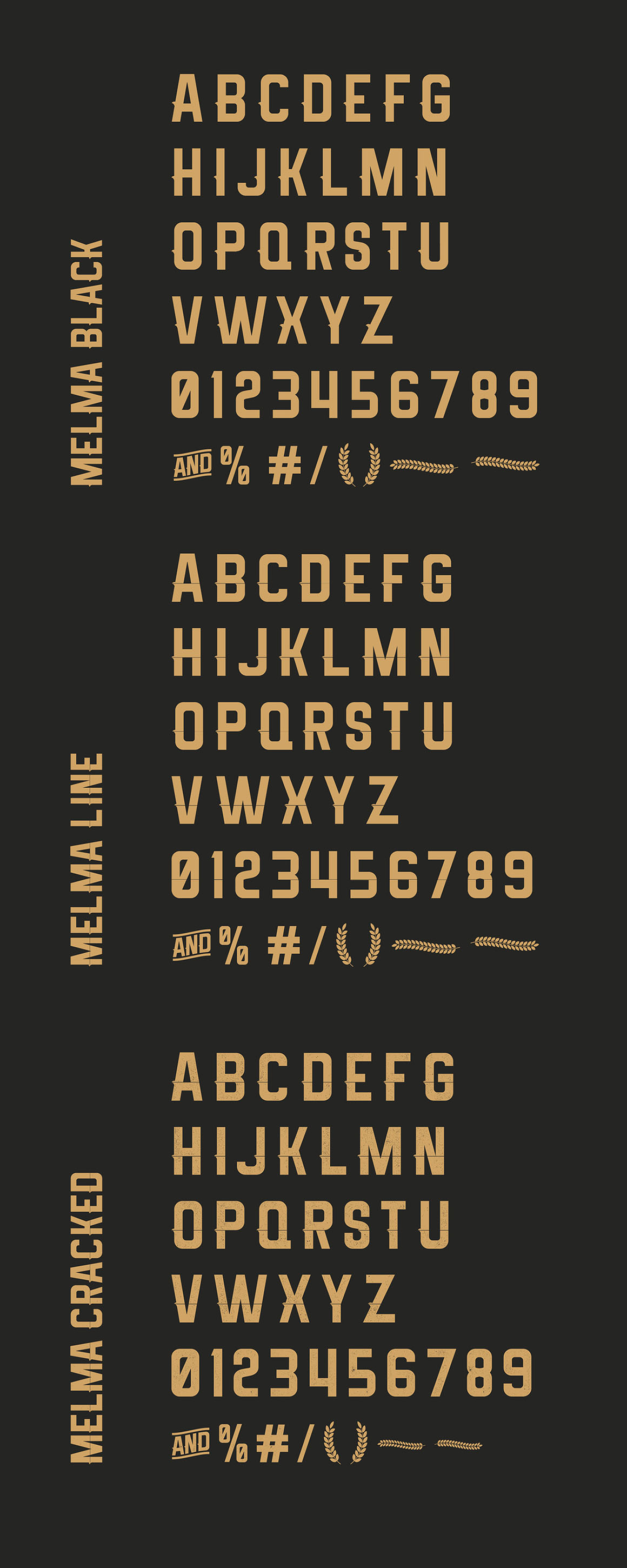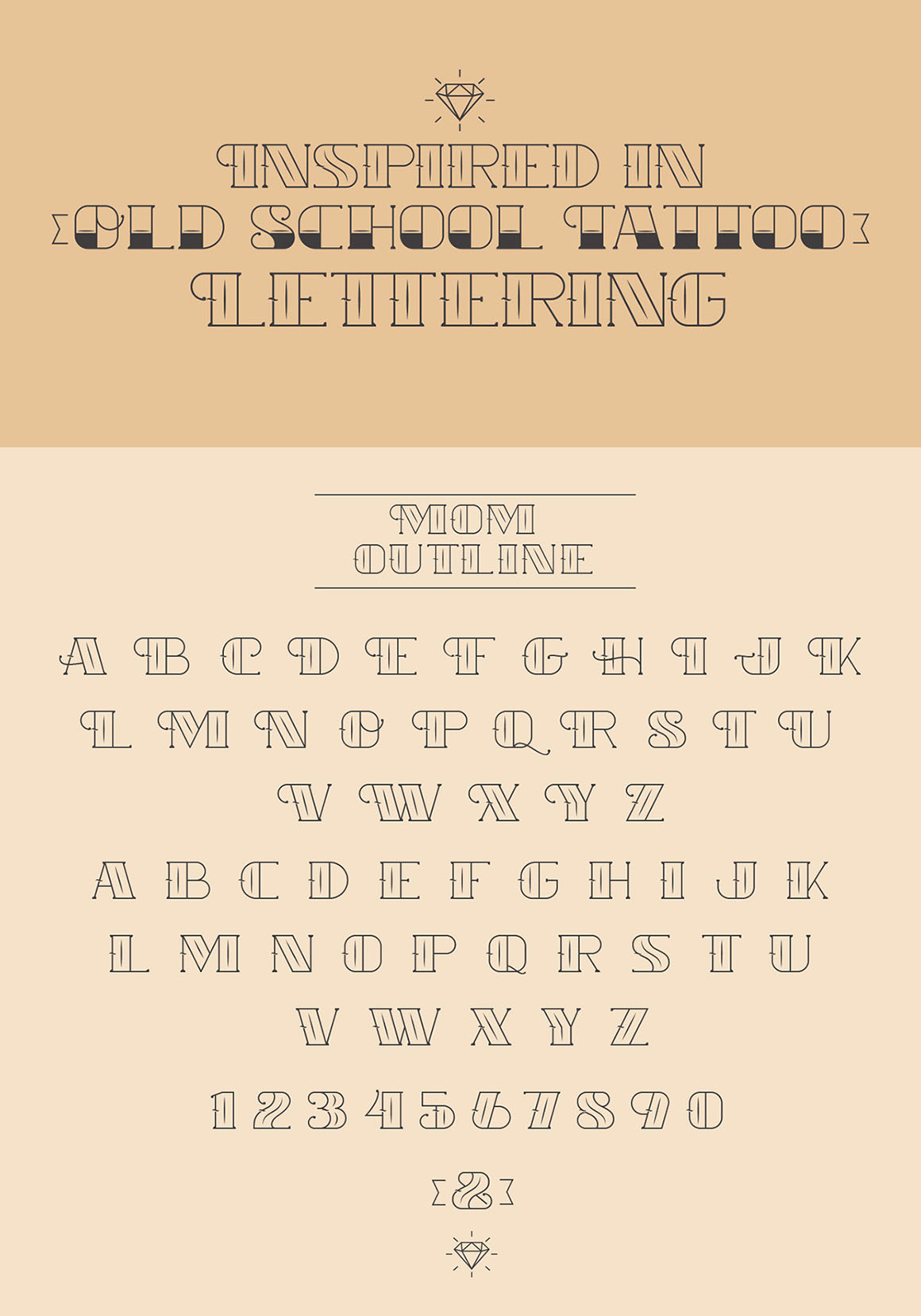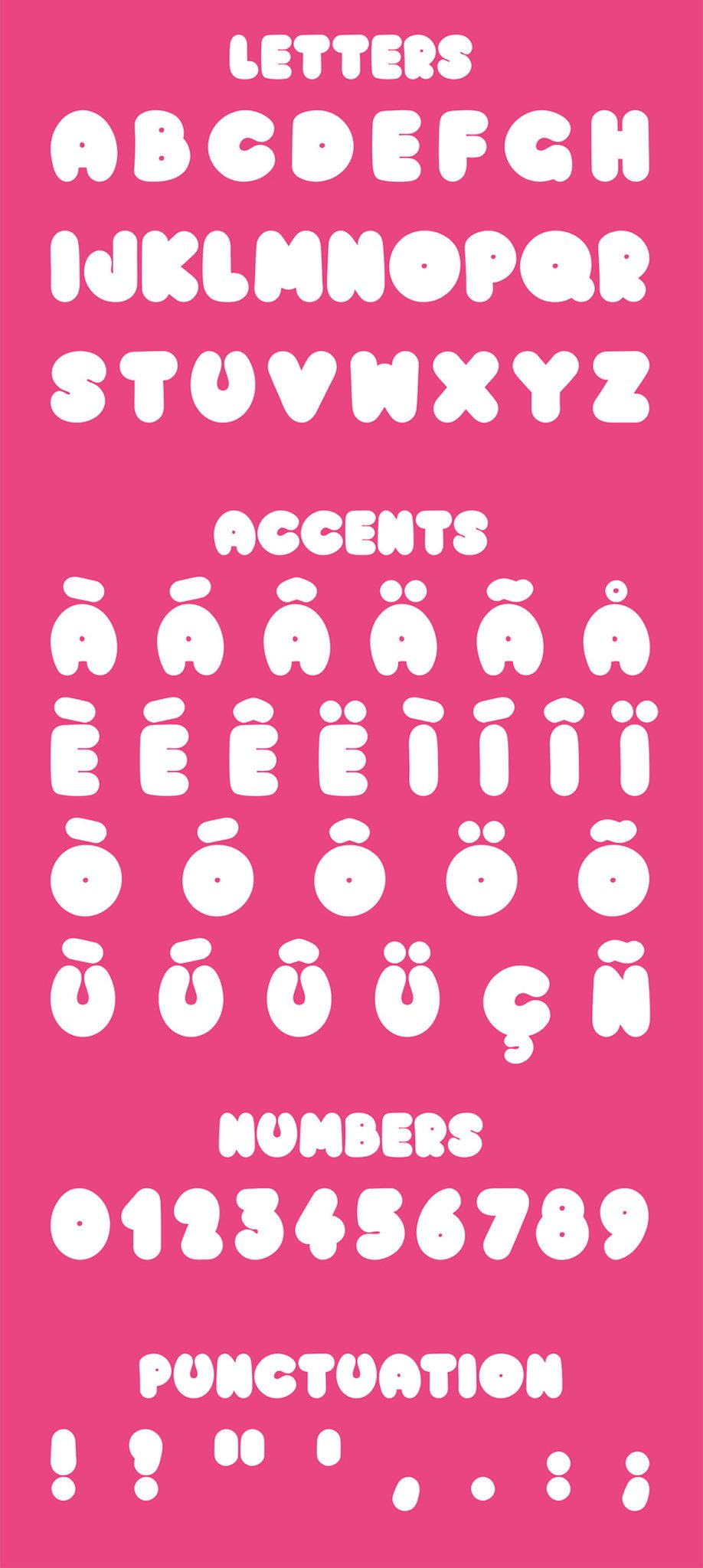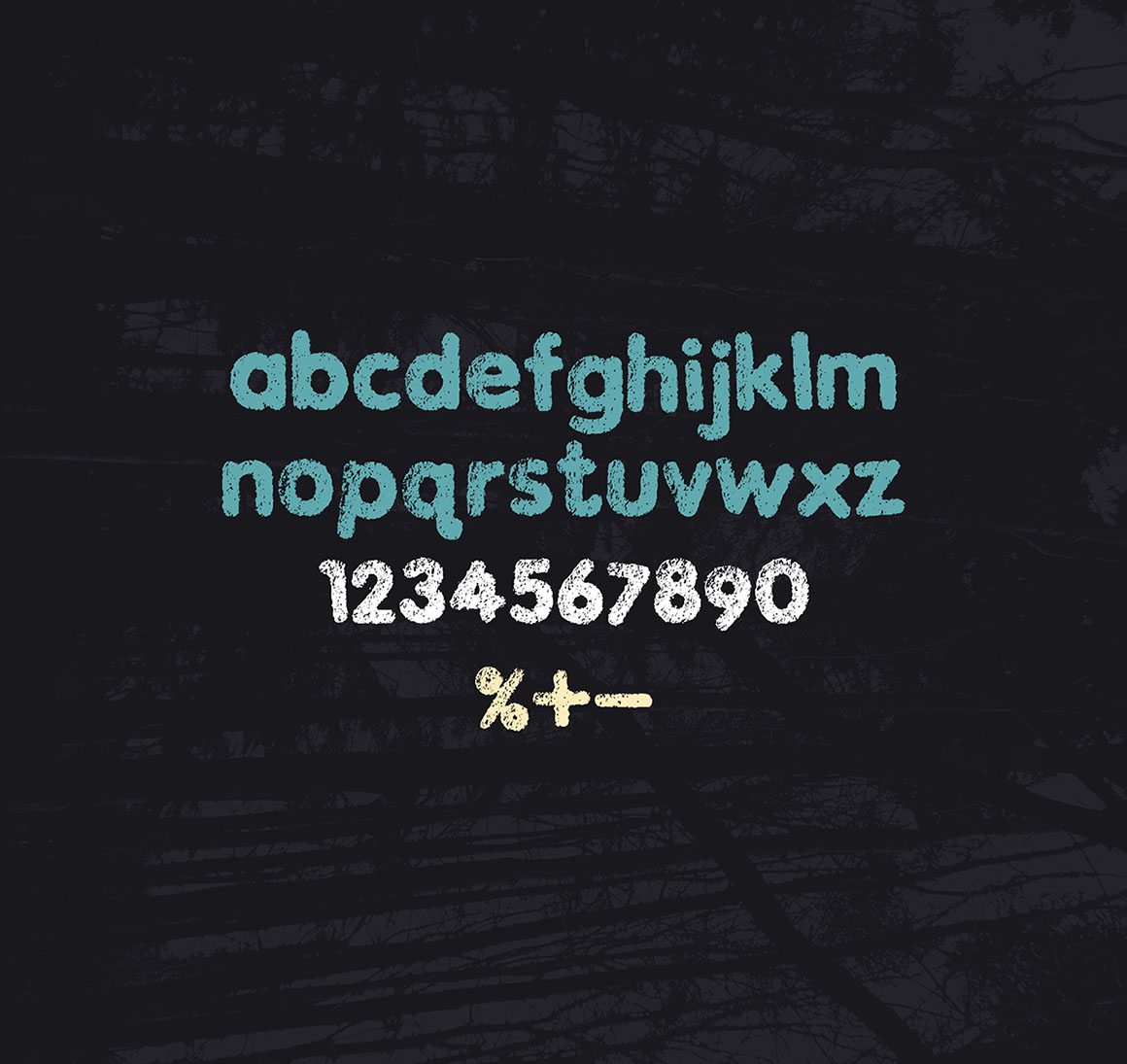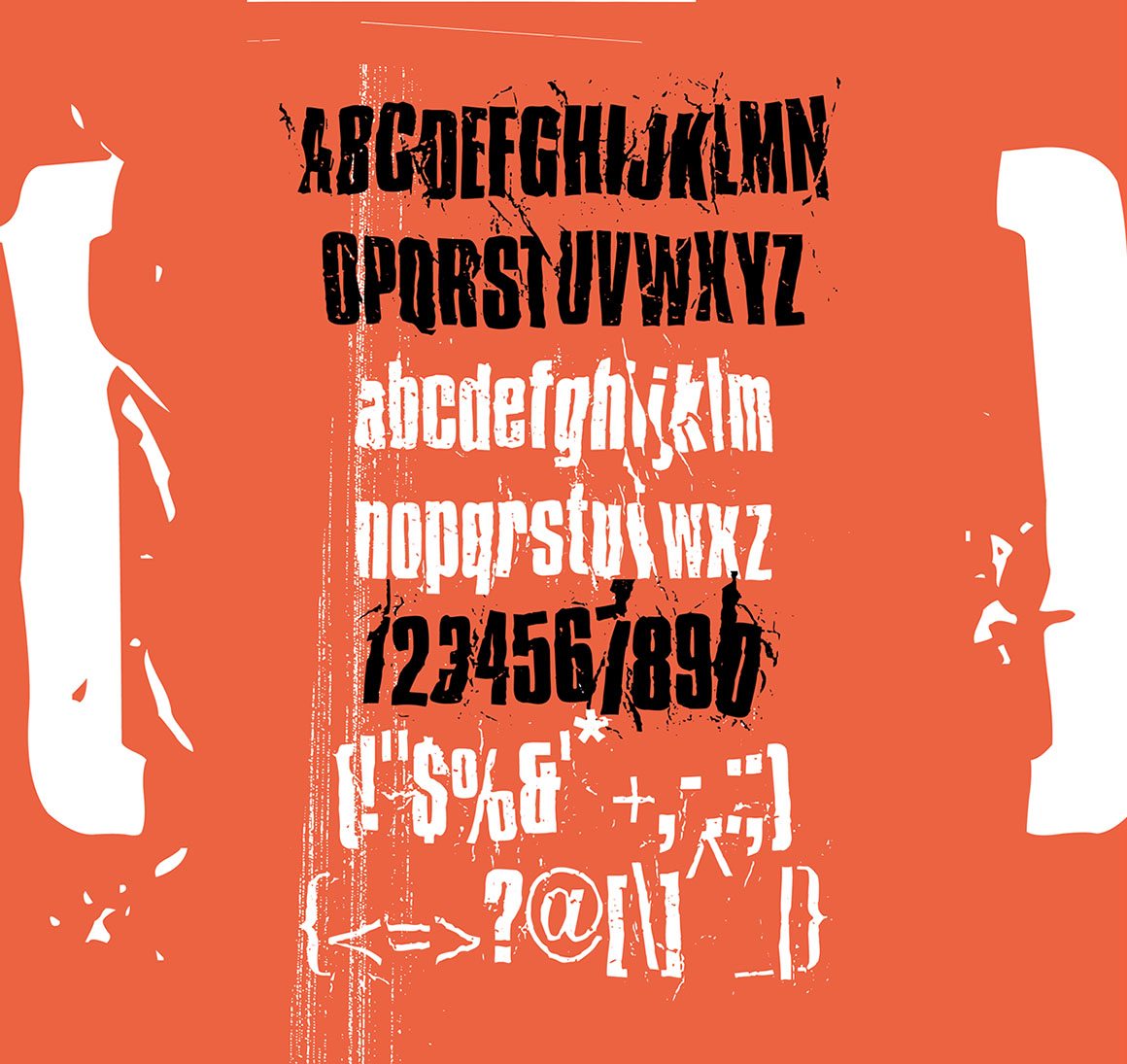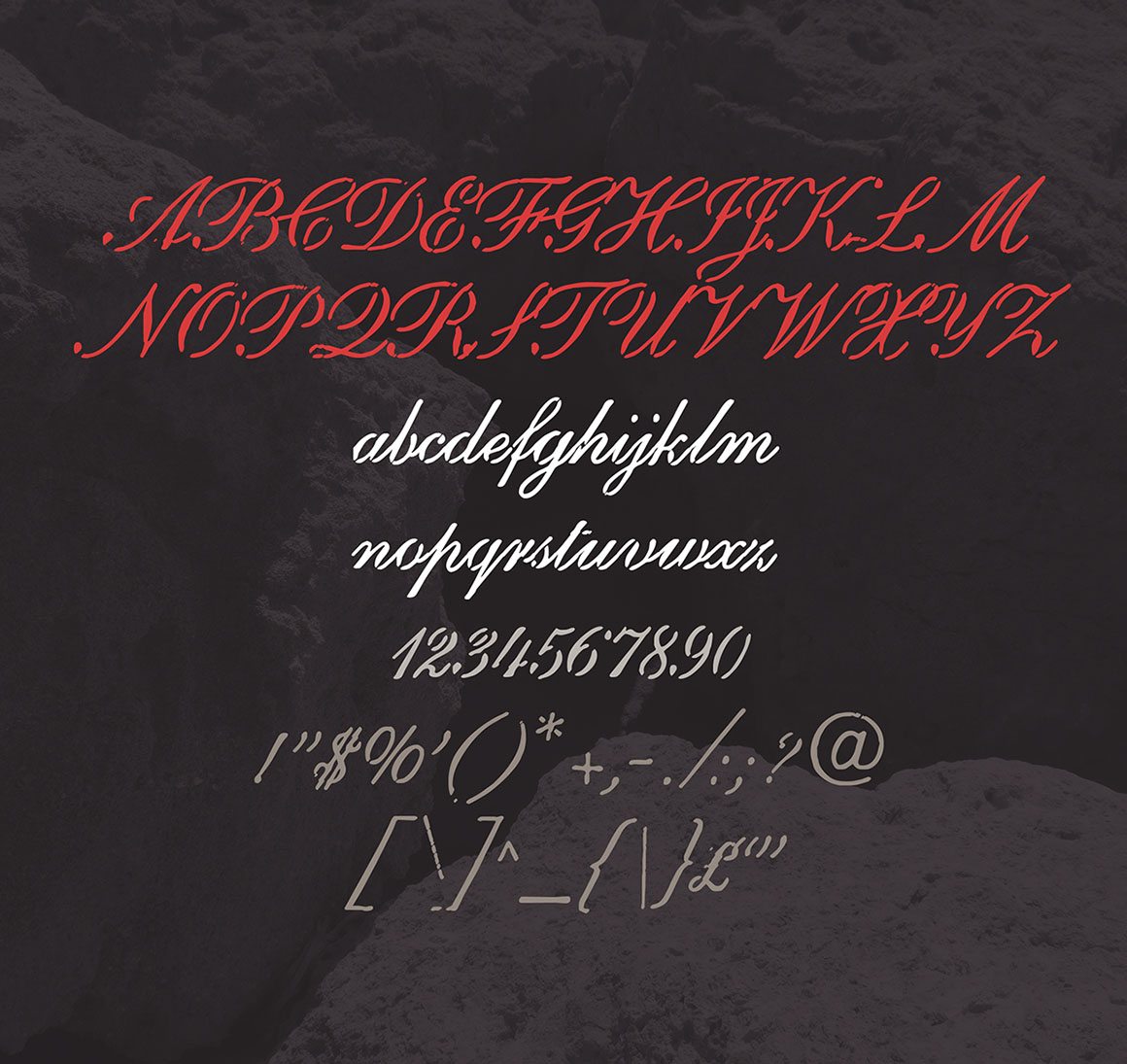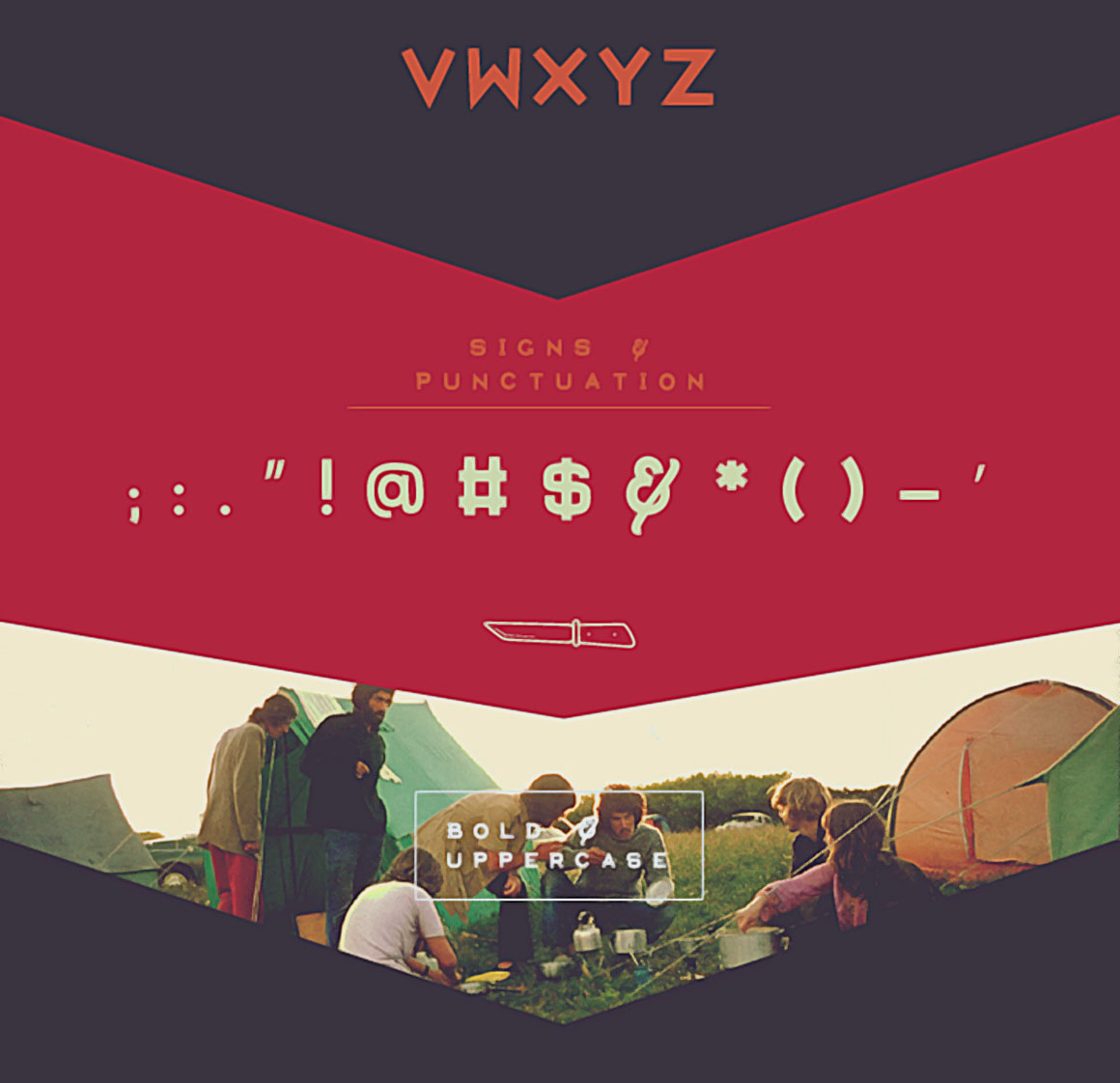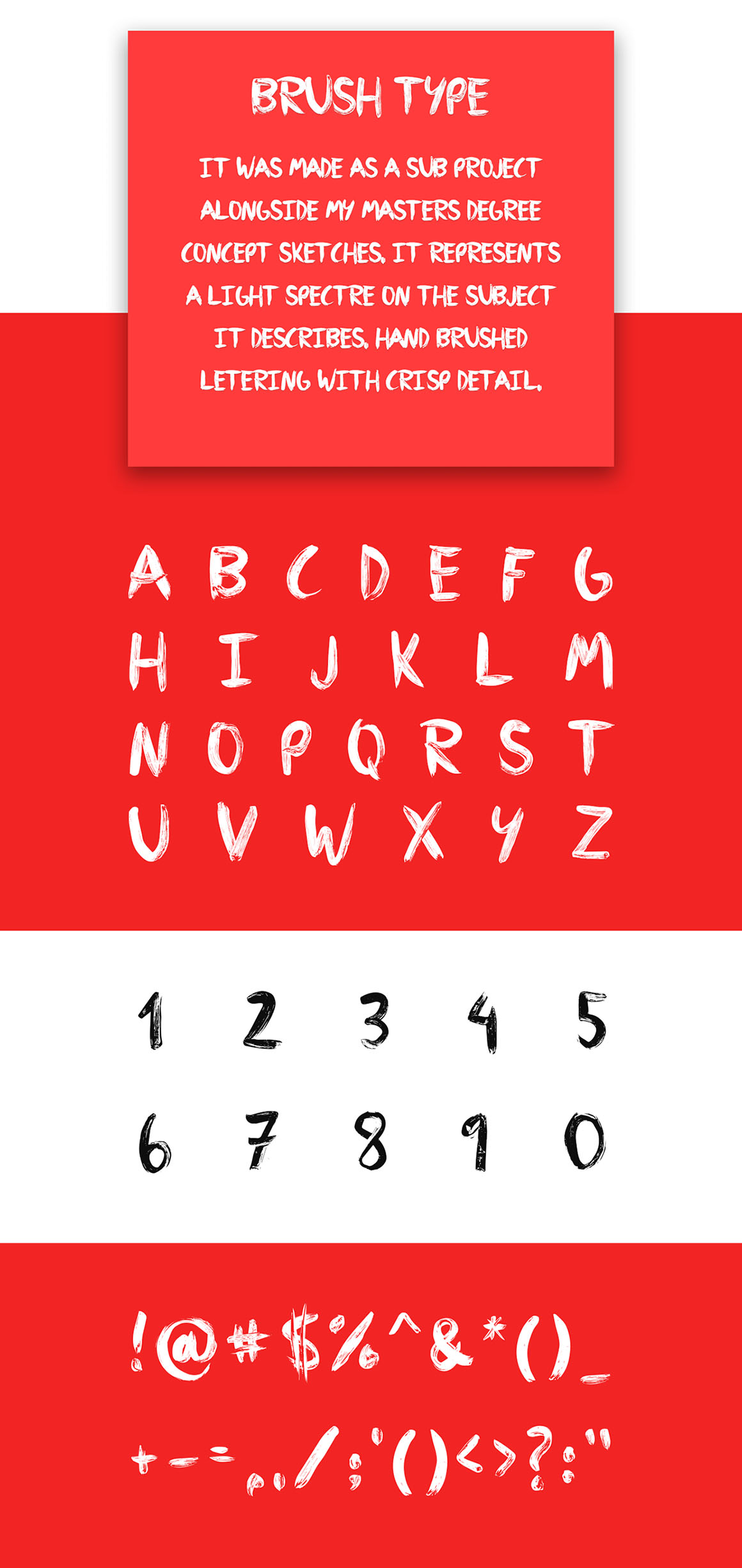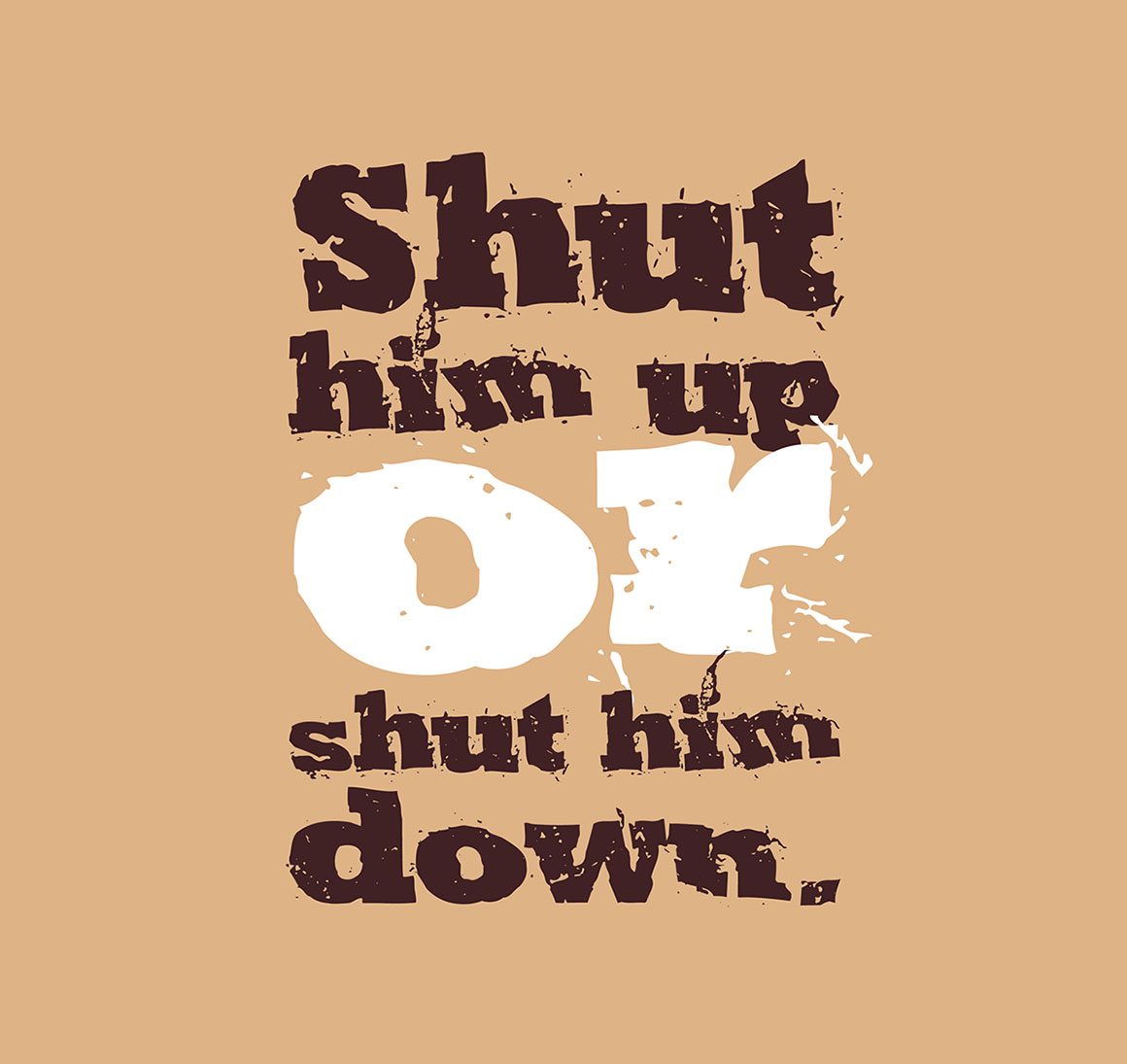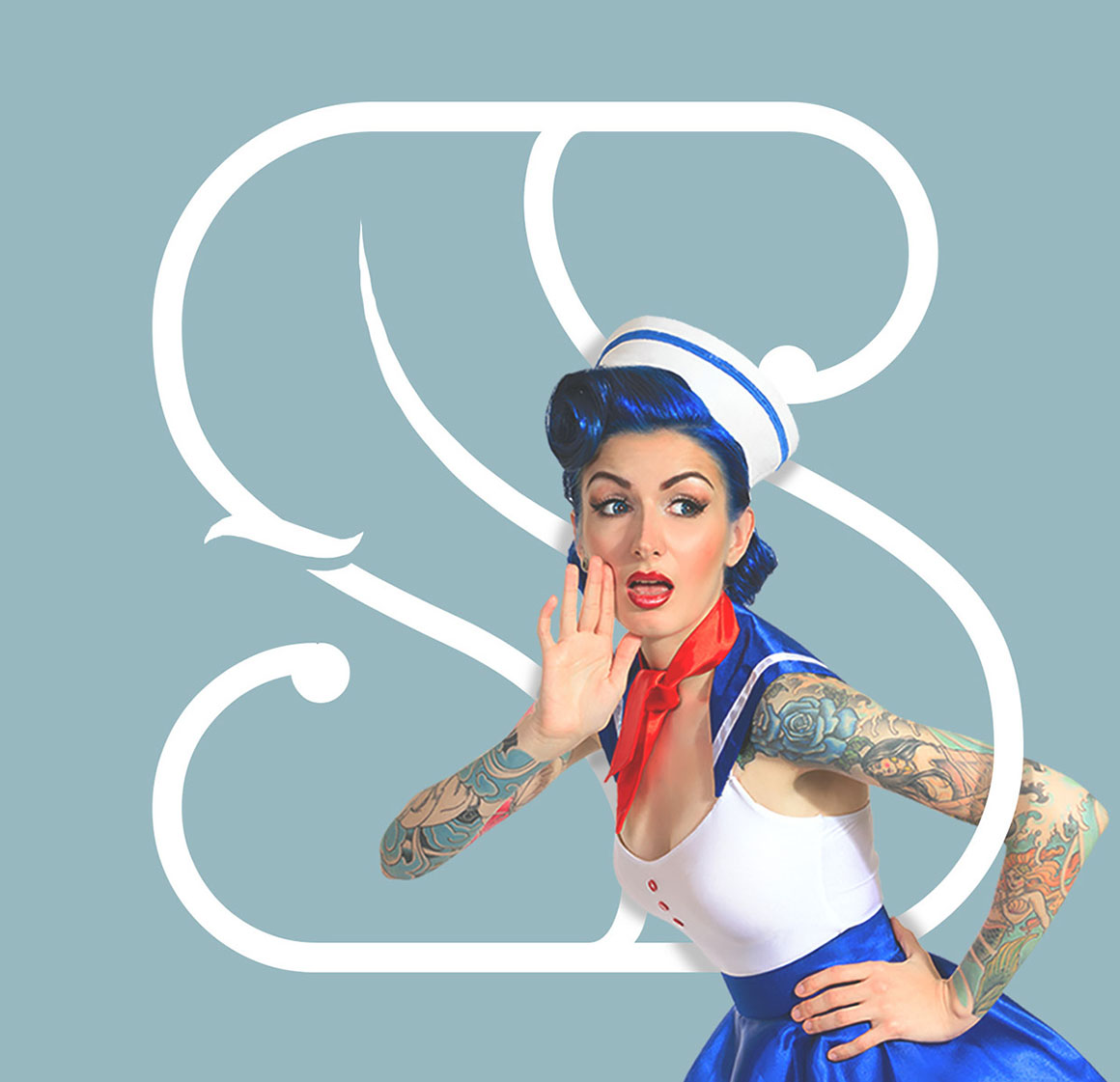
November Sources: Free font novembre 2015
1. Dreamers Brush – Free Font by Get Studio
Questo tipo di carattere tipo pennello,  freddo e urbano è di Get Studio. Ottimo per le tue nuove opere d’arte in stile creativo. Scarica e godi;)
2. Banthers – Free Vintage Font by Agga Swist’blnk
Questo font stile retrò è di Agga Swist’blnk. Un carattere tipografico con un sorprendente stile vintage tutto maiuscolo. Contenente anche un set di caratteri speciali.
3. Fabfelt – Free Script Font by Fabien Despinoy
Questo fresco carattere script gratuito, disegnato a mano, è di Fabien Despinoy.
4. Barbaro – Free Serif Font by Iván Núñez
Questo interessante tipo di carattere stile serif retrò con due varianti è di Iván Núñez
5. Tostada – Free Font by Iván Núñez
Anche questo font dal gusto retrò e di Iván Núñez.
6. Aventura – Free Bold Font by Jimmy Kalman
Questo bel font pieno e con dei bei pesi e di Jimmy Kalman.
7. Xplor – Free Typeface by Jimmy Kalman
un altro font dai toni piu leggeri di Jimmy Kalman.
8. Curely – Free Handmade Font by Konstantine Studio
Konstantine Studio ci regala questo font tutto ricci e capricci.
9. Furgatorio – Free Font by Aaron Amar
Una via di mezzo tra un font retrò e un font da super eroi di Aron Amar.
10. Melma – Free Font by Rafa Miguel
Un gusto caraibico per questo font di Rafa Miguel, che ha ben 3 varianti.
11. Mom – Free Retro Font by Rafa Miguel
Un altro font molto interessante,tattoo style, di Rafa Miguel, con due varianti.
12. Variane – Free Script Font by Boy Moch Tomi
Script font di Boy Moch Tomi.
13. Pelemeshka – Free Font by Cyril Mikhailov
Un font morbido e soft di Cyril Mikhailov.
14. Fonarto – Free Sans Serif Font by Locomotype
Un font serif con un tocco in più di Arwan Sutanto – Locomotype.
15. Dpopper – Free Font by Iordanis Passas
Un pop and funny font di Iordanis Passas.
16. Plume – Free Brush Font by Krisjanis Mezulis & Gatis Vilaks
Un font che di pennellate ne capisce di Krisjanis Mezulis & Gatis Vilaks
17. Ikra Slab – Free Font by Sergey Godovalov
Un font serif geometrico con gusto di Sergey Godovalov.
18. Kagura – Free Font by Ezeqviel Ergo
Un font dal forte impatto di Ezeqviel Ergo.
19. Kohta – Free Fontby Ezeqviel Ergo
Ancora un font di Ezeqviel Ergo.
20. Signify – Free Handmade Font by Conor Leary
Un font pieno ma morbido come un pennarello di Conor Leary.
21. Chubby – Free Funny Font by Andrea Prina